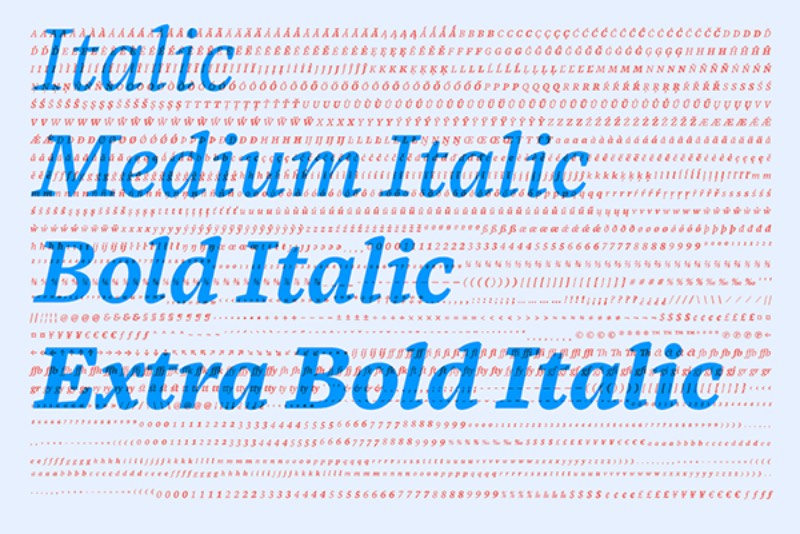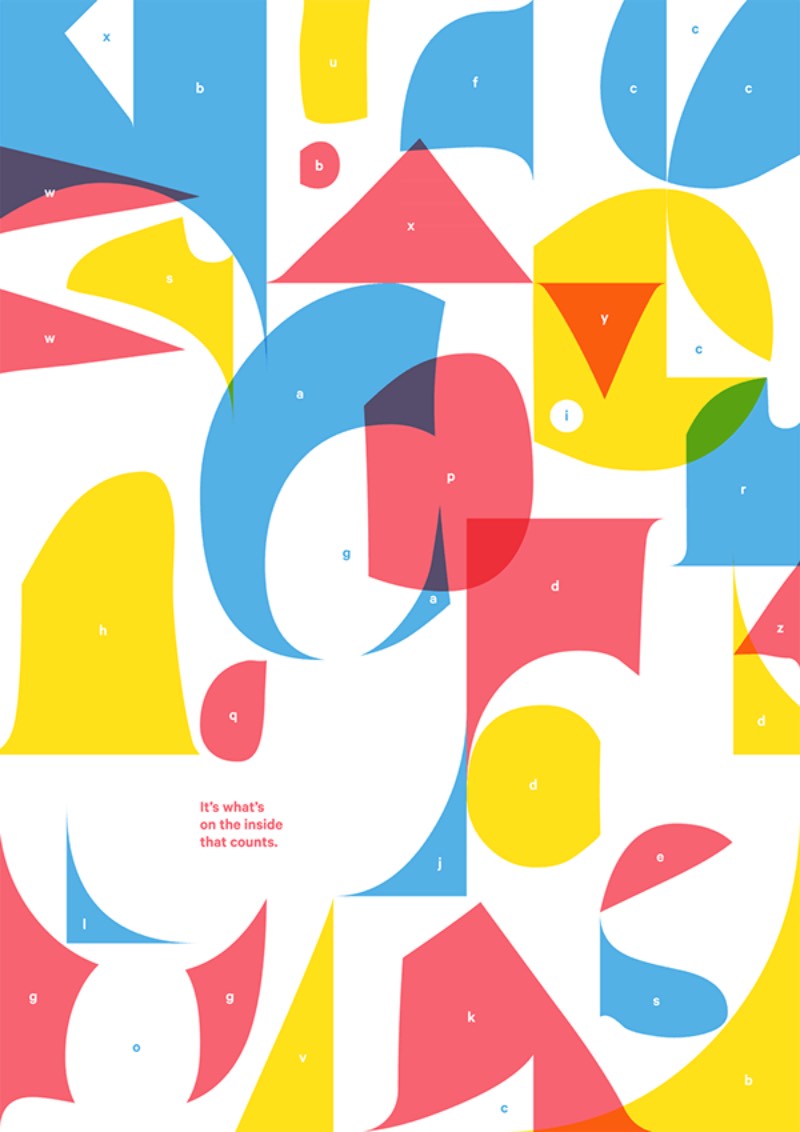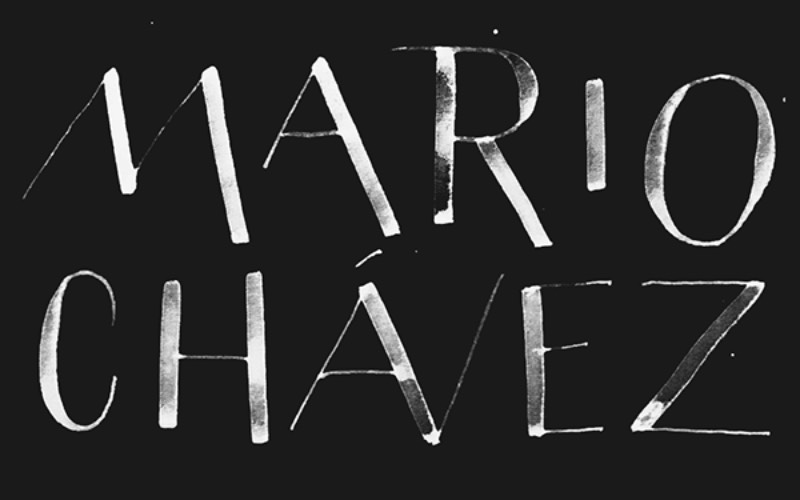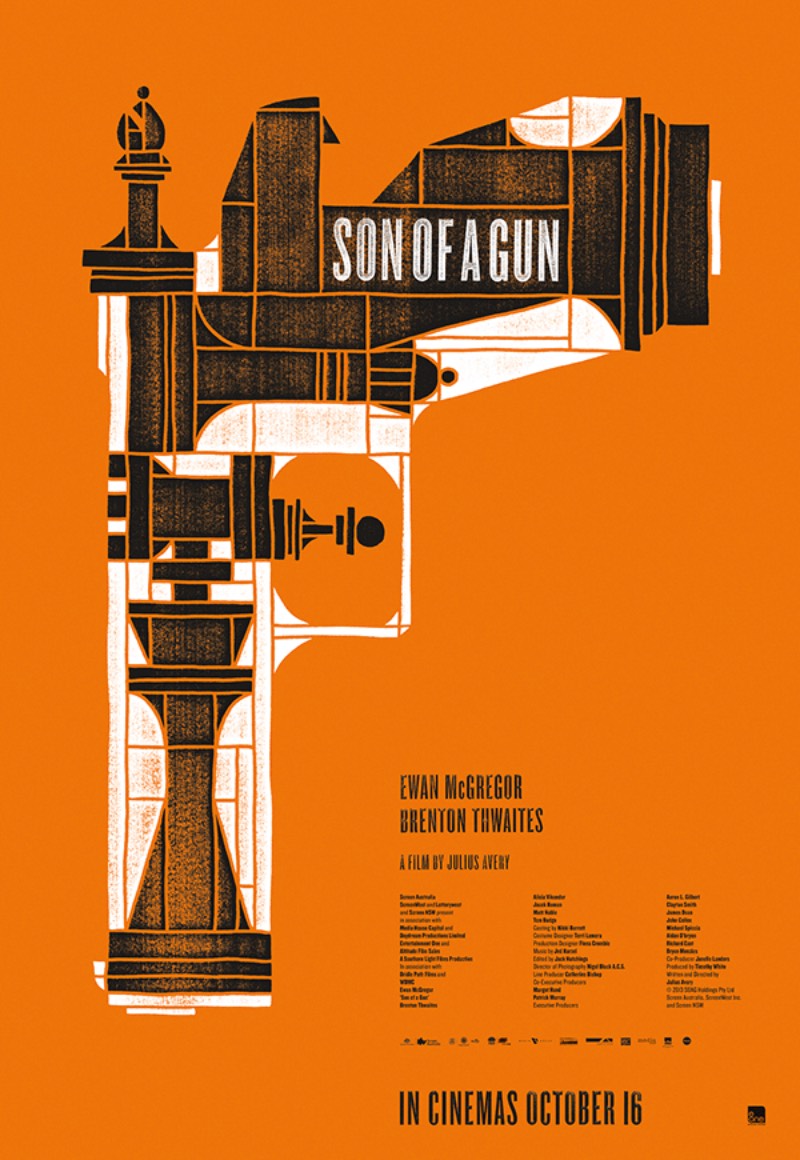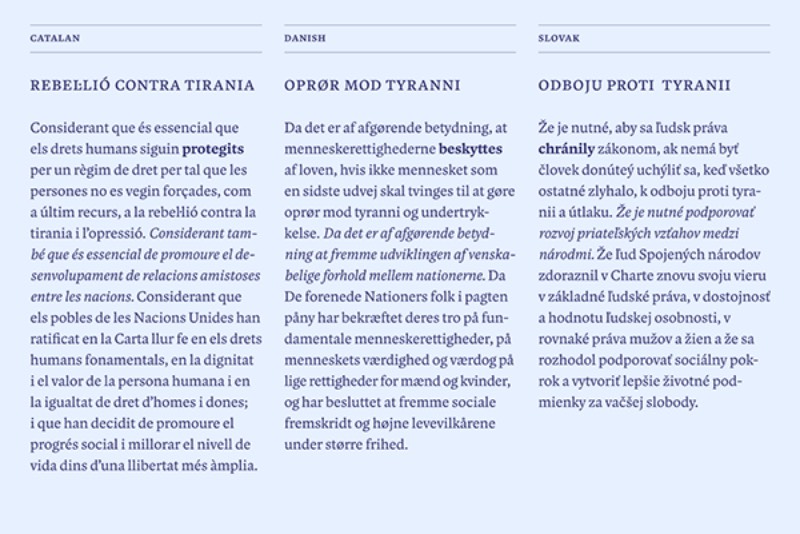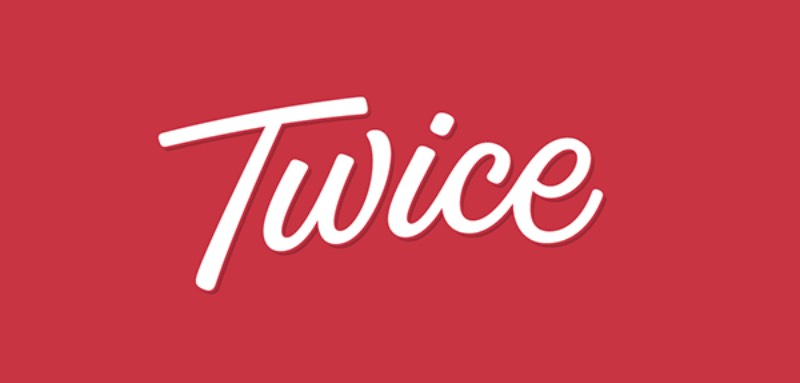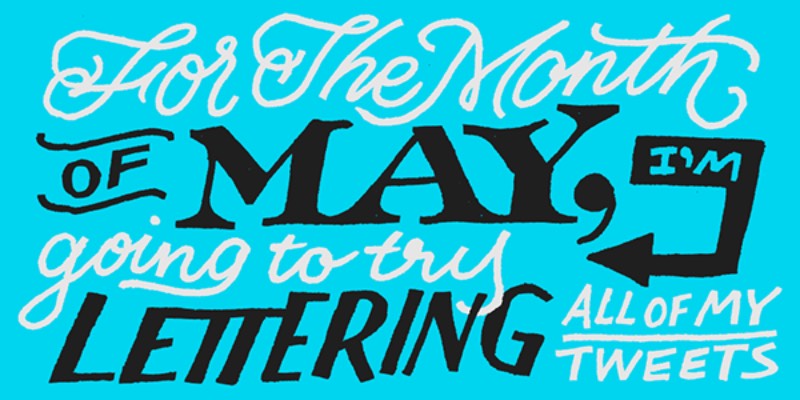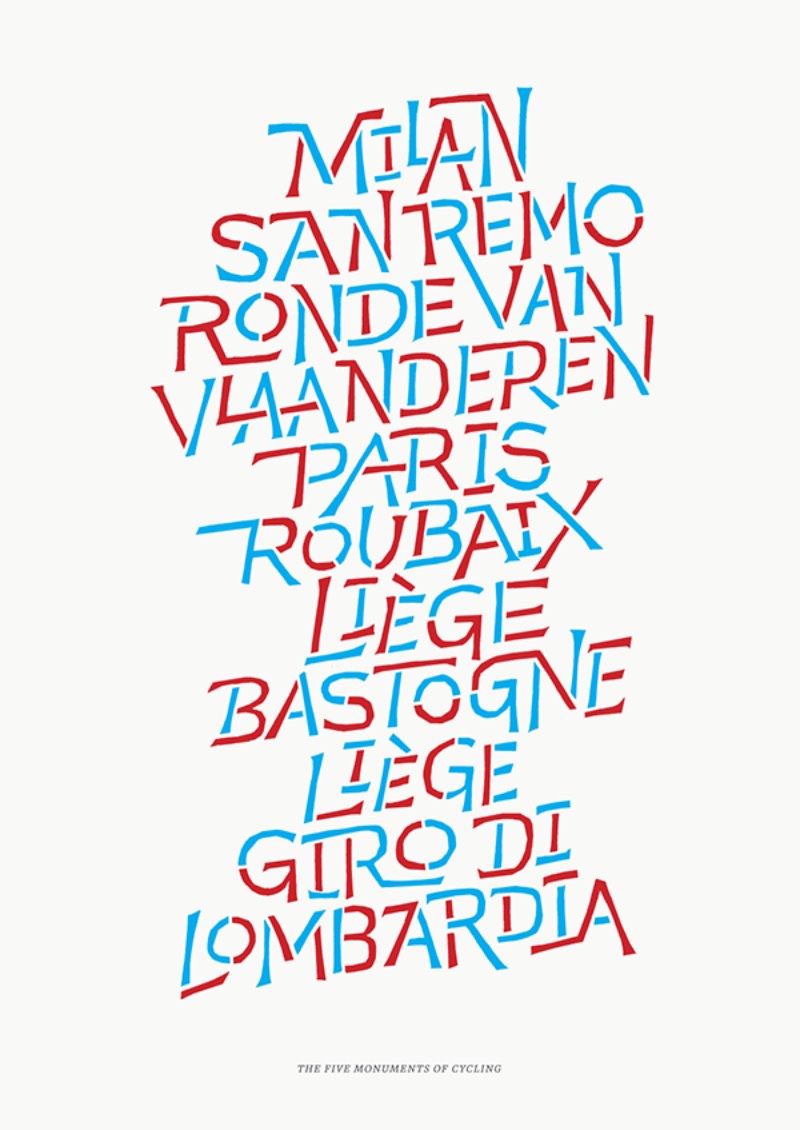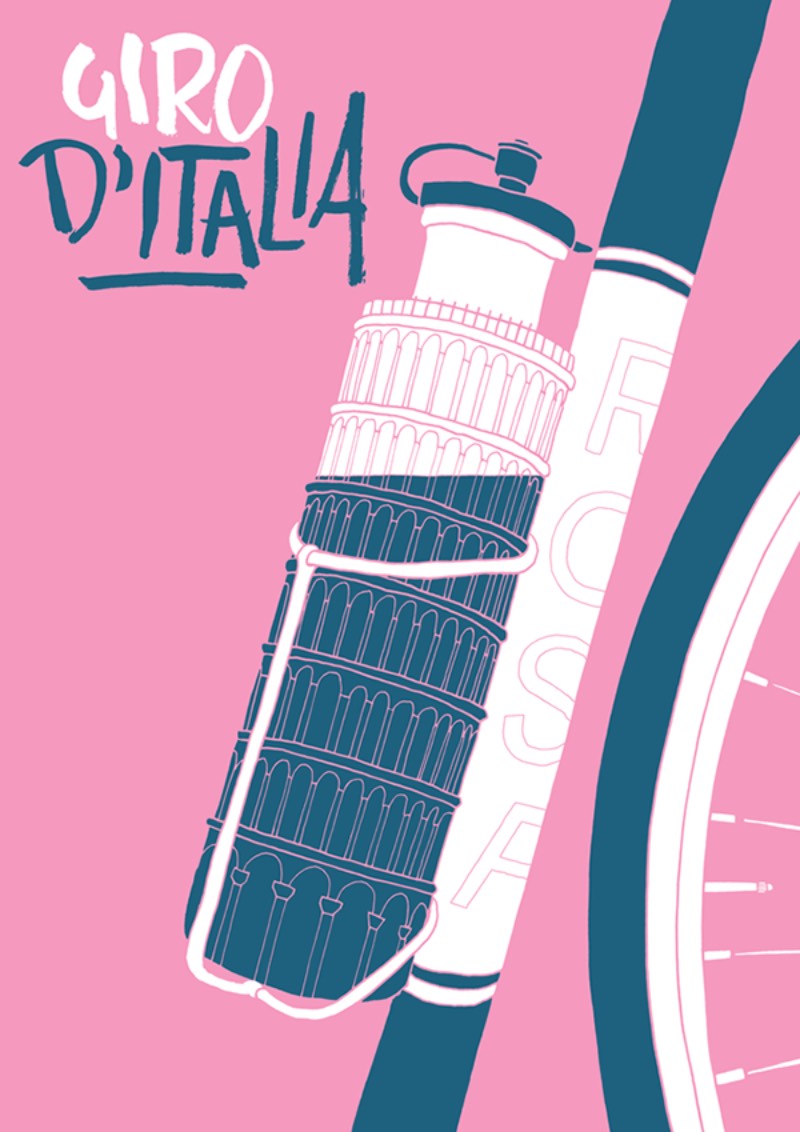
Foster Type: O Trabalho de Tipografia de Dave Foster
Foster Type é o nome que Dave Foster resolveu adotar para seu trabalho de tipografia e design. Trabalhando de forma independente lá de Sydney, na Austrália, ele cria fontes e lettering para estúdios de design, empresas que trabalham com tipografia, marcas e outros clientes ao redor do mundo.
Dave Foster acredita que uma presença visual poderosa é algo mais do que necessário para que qualquer mensagem possa sobreviver ao barulho e ao excesso de informações em que vivemos hoje em dia. É por isso que ele foca seu trabalha na Foster Type em dar uma durabilidade a forma que as palavras precisam ter para emanar uma presença forte. E ele faz isso usando apenas letras ou alfabetos completos, seu objetivo é sempre o de usar da tipografia para solucionar problemas específicos.
Quando você dá uma olhada no extenso portfólio de tipografia da Foster Type, uma fonte vai chamar sua atenção. Blanco foi aquela que capturou meu olhar inicialmente. Essa fonte vem com 4 pesos diferentes e tem um visual forte e consistente que cria um ritmo de leitura como um tom de voz calmo. Além disso, considero que a Blanco deve ser fácil de combinar com outras fontes, principalmente quando ela é usada no corpo de um texto.